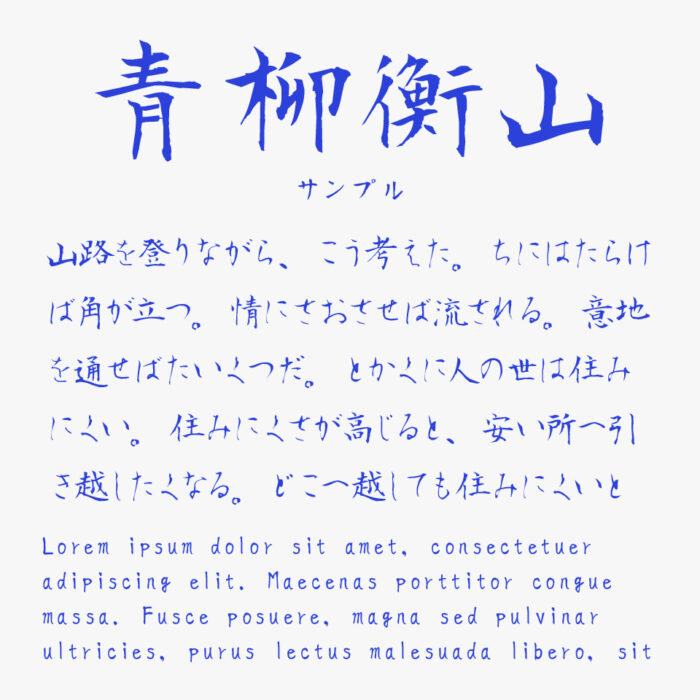
青柳衡山フォントTは、書家の青柳衡山先生が書かれた文字をベースに作成された毛筆フォントです。
一本一本の筆致に緊張感と洗練さがあり、筆文字の風合いを丁寧に活かしながらも、より引き締まった美しさを感じさせる毛筆フォントです。
やや縦長なフォルムが、より端正で凛とした佇まいな雰囲気を作り出しています。格式のある日本文化や和の世界観を表現する場面にぴったりなフォントです。